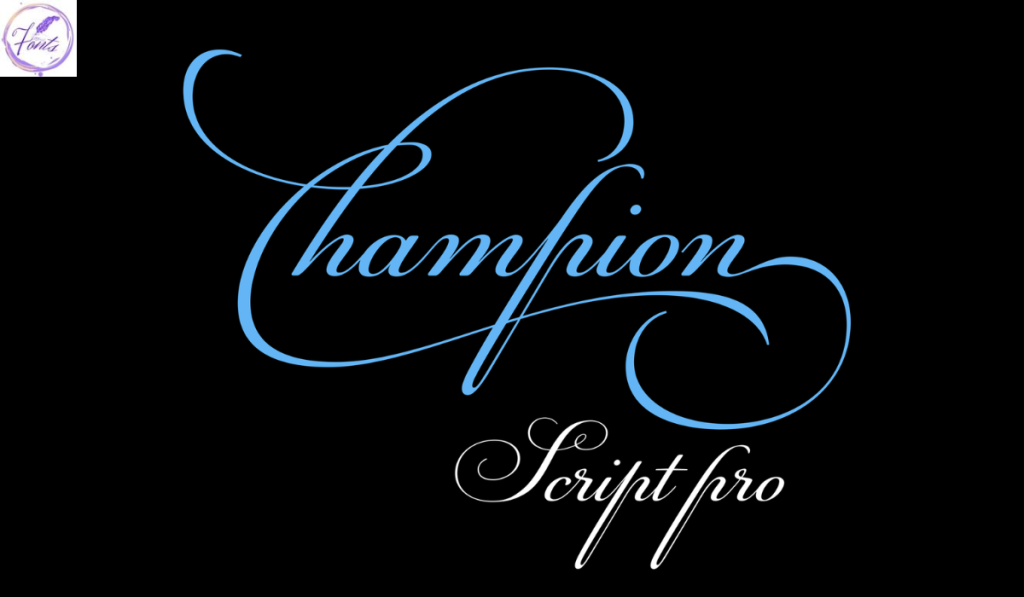
Font PF Champion Script Pro việt hóa
Bộ Font: PF Champion Script Pro
Phân loại: Cá tính, độc đáo
Kiểu chữ: Kiểu chữ viết tay
PF Champion Script Pro là một font chữ đẹp mắt, nổi bật với phong cách viết tay cổ điển nhưng không kém phần hiện đại. Được phát triển bởi Panos Vassiliou vào năm 2016, font chữ này nổi bật với sự kết hợp giữa các đường nét thanh mảnh và dày đậm, tạo nên một cảm giác tinh tế và sang trọng. PF Champion Script Pro đặc biệt phù hợp cho các dự án thiết kế như logo, tiêu đề, và thiệp mời, mang đến vẻ đẹp cổ điển và phong cách.
Đánh giá pf champion script pro
PF Champion Script Pro nhận được nhiều lời khen ngợi từ các nhà thiết kế và người dùng nhờ vào sự linh hoạt và thẩm mỹ của nó. Điểm nổi bật của font chữ này là bộ ký tự đầy đủ và phong phú, bao gồm các chữ cái hoa, thường và các ký tự đặc biệt. Đặc biệt, phiên bản pf champion script pro bold giúp tạo điểm nhấn mạnh mẽ trong các thiết kế. Được đánh giá cao về độ dễ đọc và tính ứng dụng, PF Champion Script Pro là lựa chọn tuyệt vời cho bất kỳ dự án thiết kế nào.